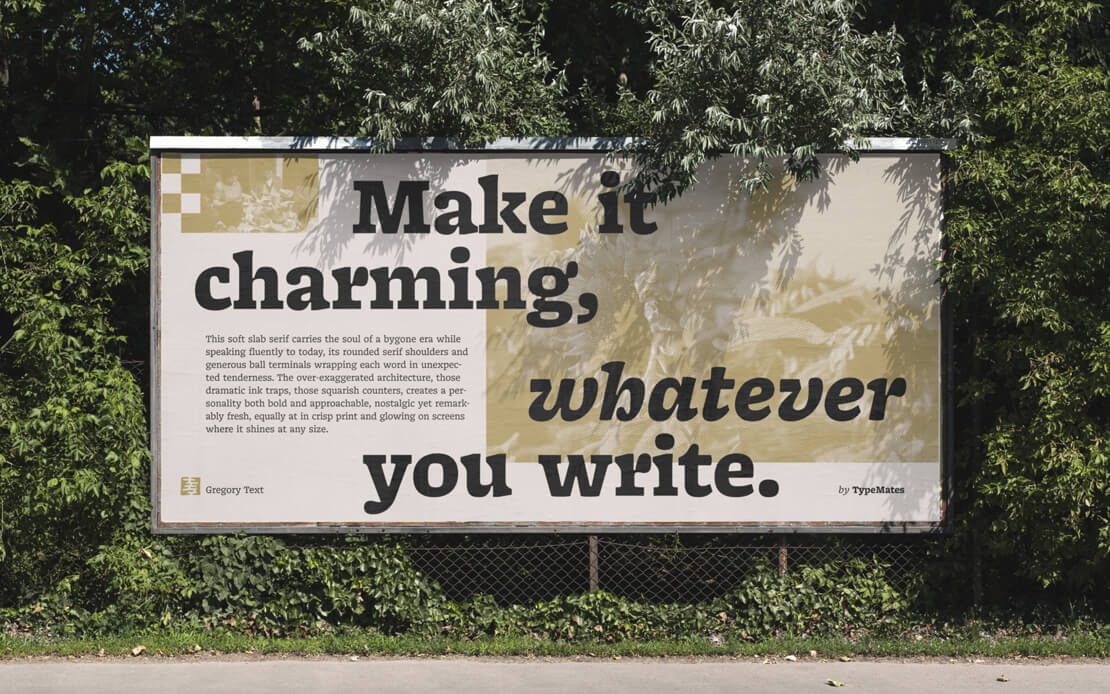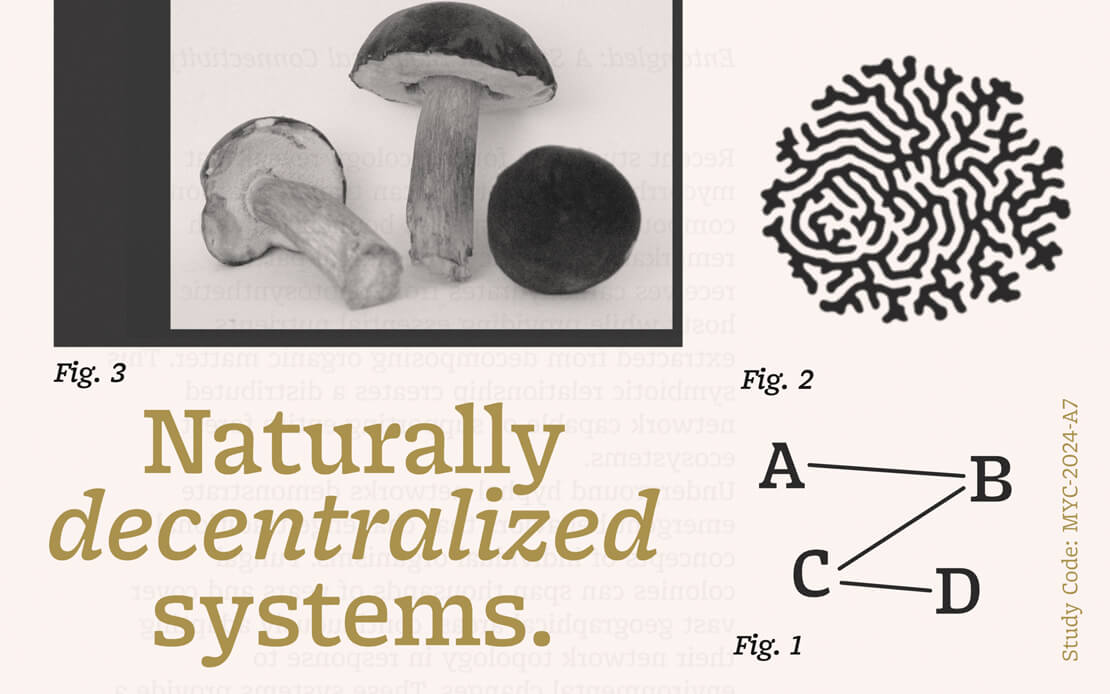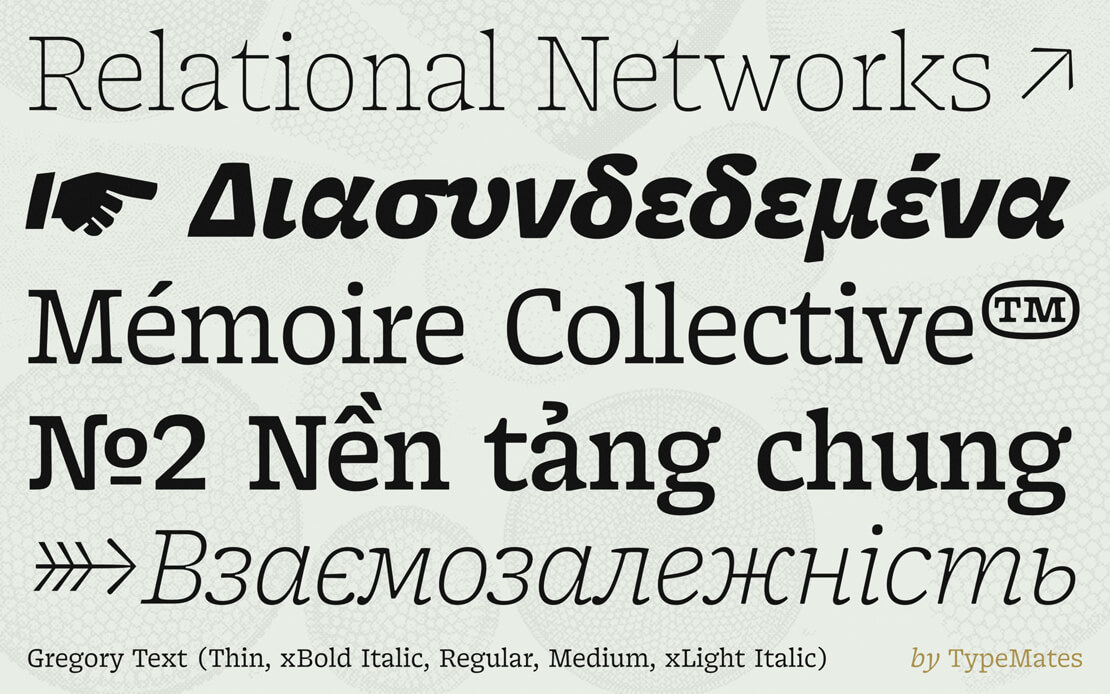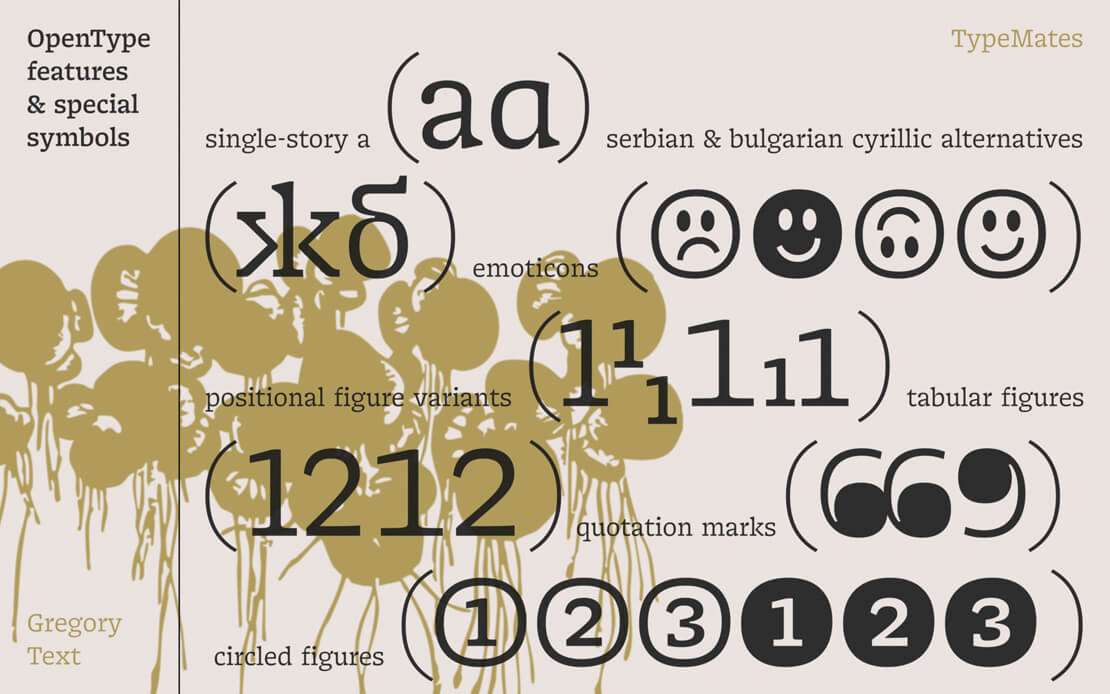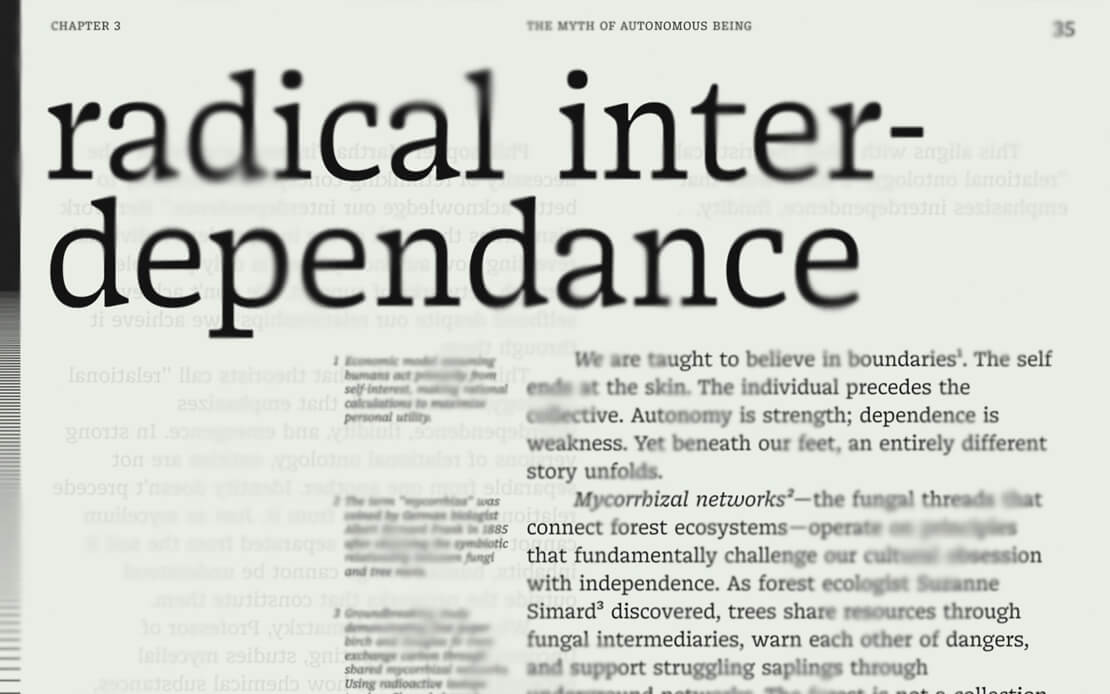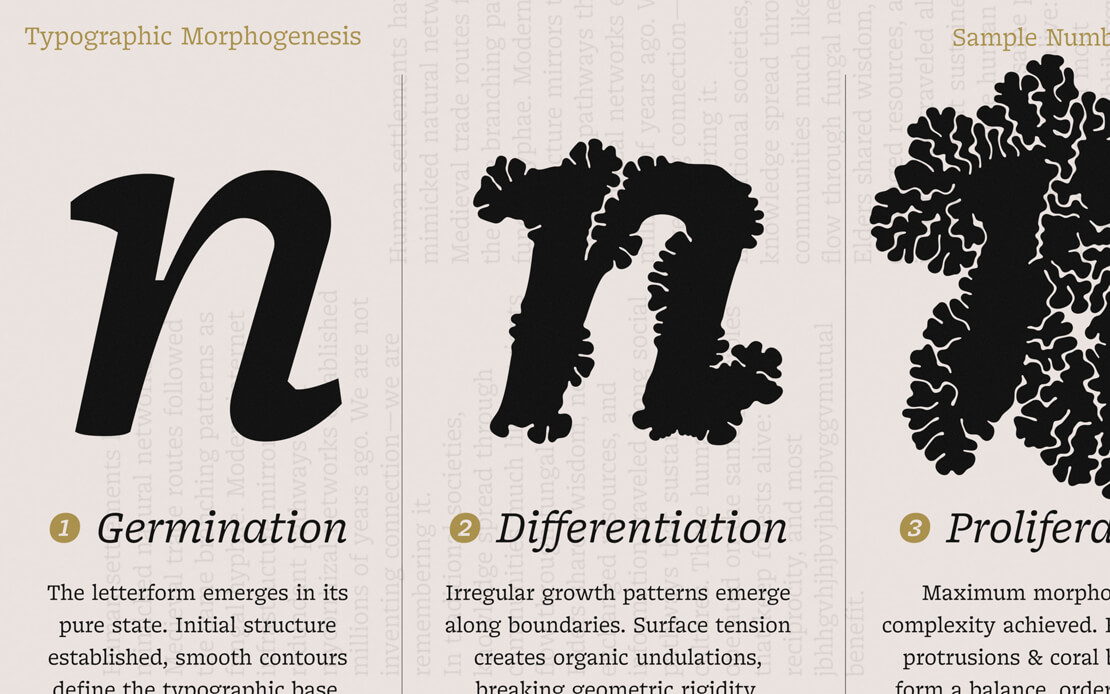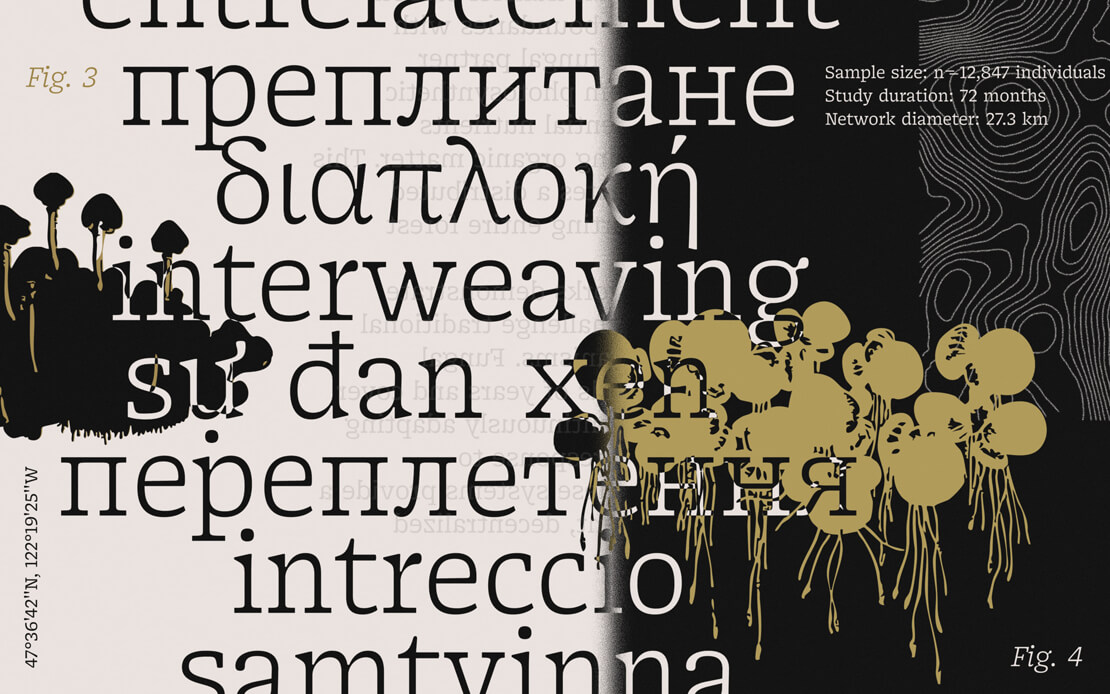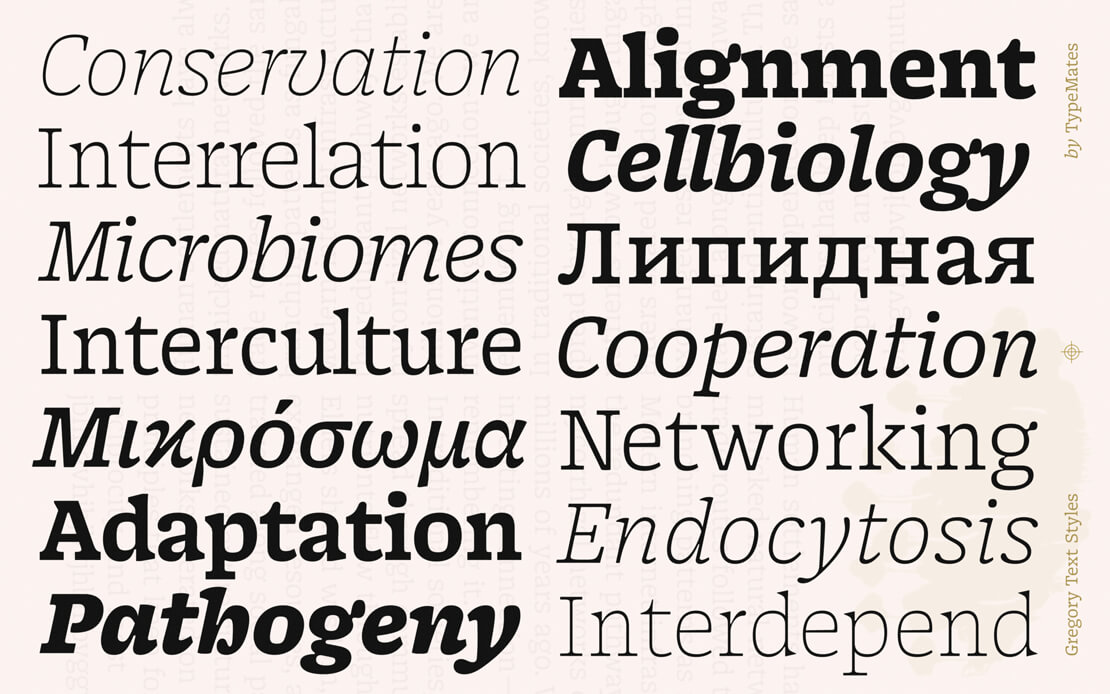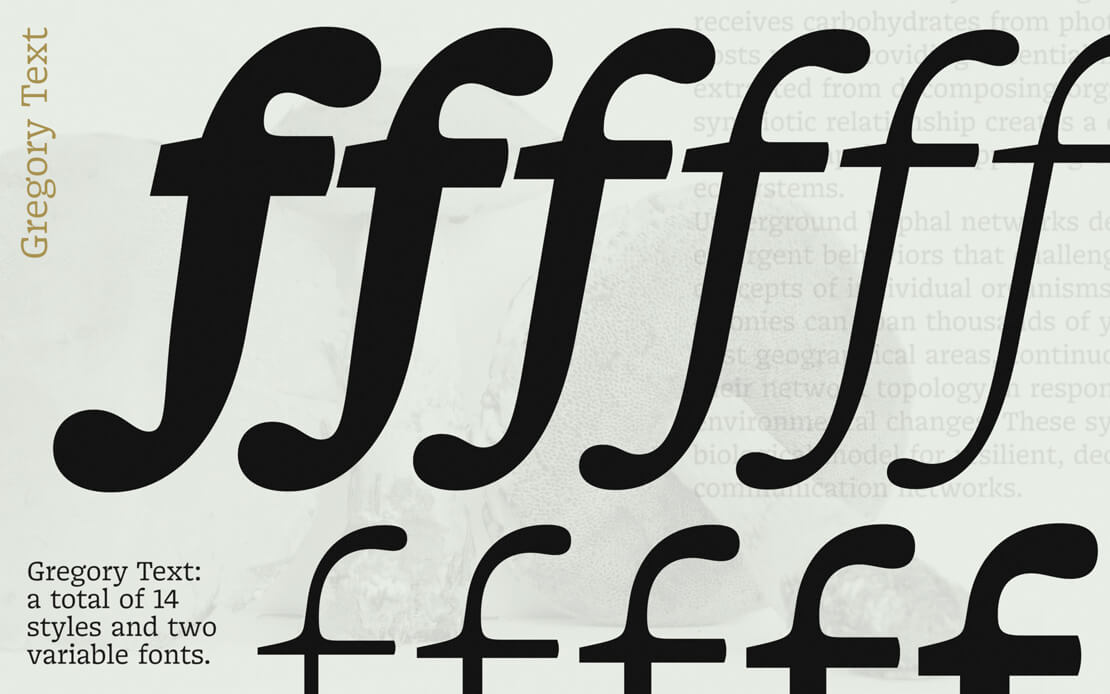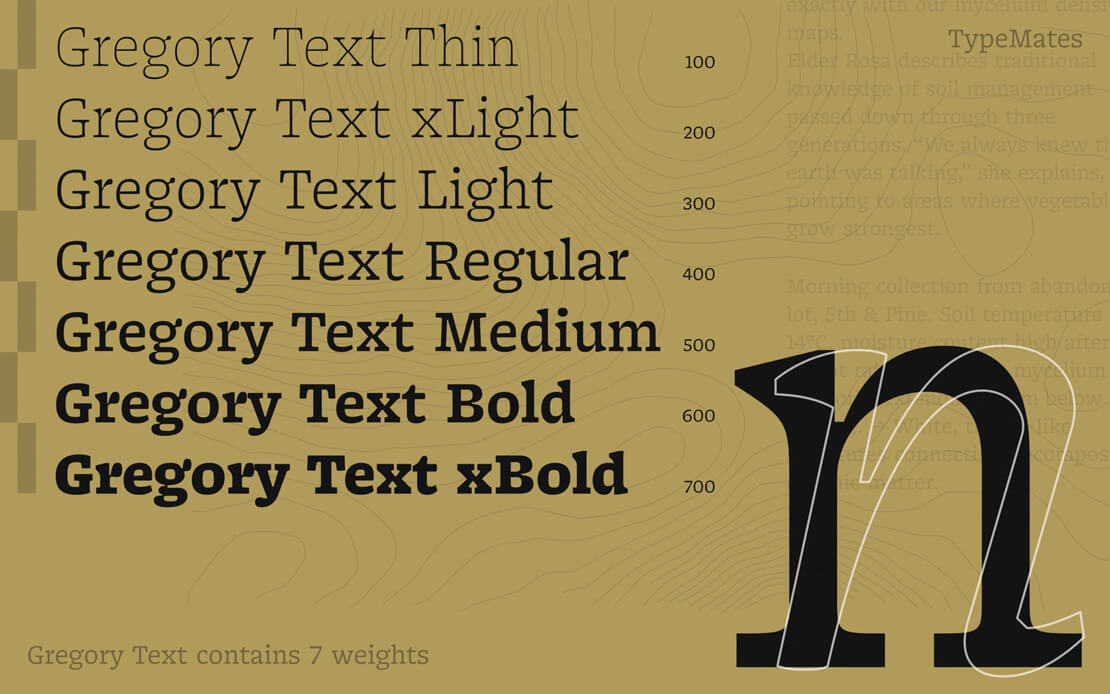
»Gregory Text« bei TypeMates erschienen
Die Foundry TypeMates präsentiert eine neue Slab-Serif-Schriftart. Der Entwurf kombiniert historische Vorbilder aus dem Bleisatz mit zeitgenössischen Proportionen und markanten Details.
Mit der Gregory Text veröffentlicht das Label TypeMates eine Schriftfamilie für die typografische Textgestaltung. Das Design von Jakob Runge, George Triantafyllakos und Seryozha Rasskazov interpretiert die Ästhetik historischer Slab-Serifs neu. Dabei verzichtet der Entwurf auf eine streng kühle Geometrie und setzt stattdessen auf handgemachte Details sowie warme und auffällige Akzente.
Gestaltungsprinzip für den Micro-Text
Um eine klare Erkennbarkeit in sehr kleinen Schriftgraden zu gewährleisten, greift die Gestaltung auf die sogenannte M-Formel von W. A. Dwiggins zurück. Dieses Prinzip arbeitet mit betonten Kanten, verstärkten Details und überzeichneten Binnenformen. Durch diese prägnanten Gestaltungsmerkmale entfalten die Zeichen jedoch auch in großen Formaten und in Überschriften eine eigene Wirkung.
Die zugehörigen kursiven Schnitte sind von beherzt kantig geschwungenen Formen geprägt, um eine lebendige, aber strapazierfähige Textur im Mengensatz zu erzeugen.
Zeichenumfang und Superfamilie
Die Gregory Text ist technisch umfangreich ausgebaut: Sie unterstützt über 270 Sprachen. Die griechischen und kyrillischen Zeichen wurden dabei von Muttersprachlern entworfen; zudem ist Vietnamesisch enthalten. OpenType-Features bieten Zugriff auf verschiedene Ziffernsätze – darunter Mediävalziffern –, sprachspezifische Varianten sowie diverse Symbole und Emojis.
Die Schrift reiht sich zudem in die übergeordnete Gregory-Kollektion ein. Diese umfasst neben der Text-Variante auch die »Gregory Poster« und die »Gregory Grotesk«. Die Familienmitglieder teilen eine gemeinsame Grundausstrahlung, wurden in ihrer konkreten Ausarbeitung jedoch als eigenständige Gestaltungen angelegt.